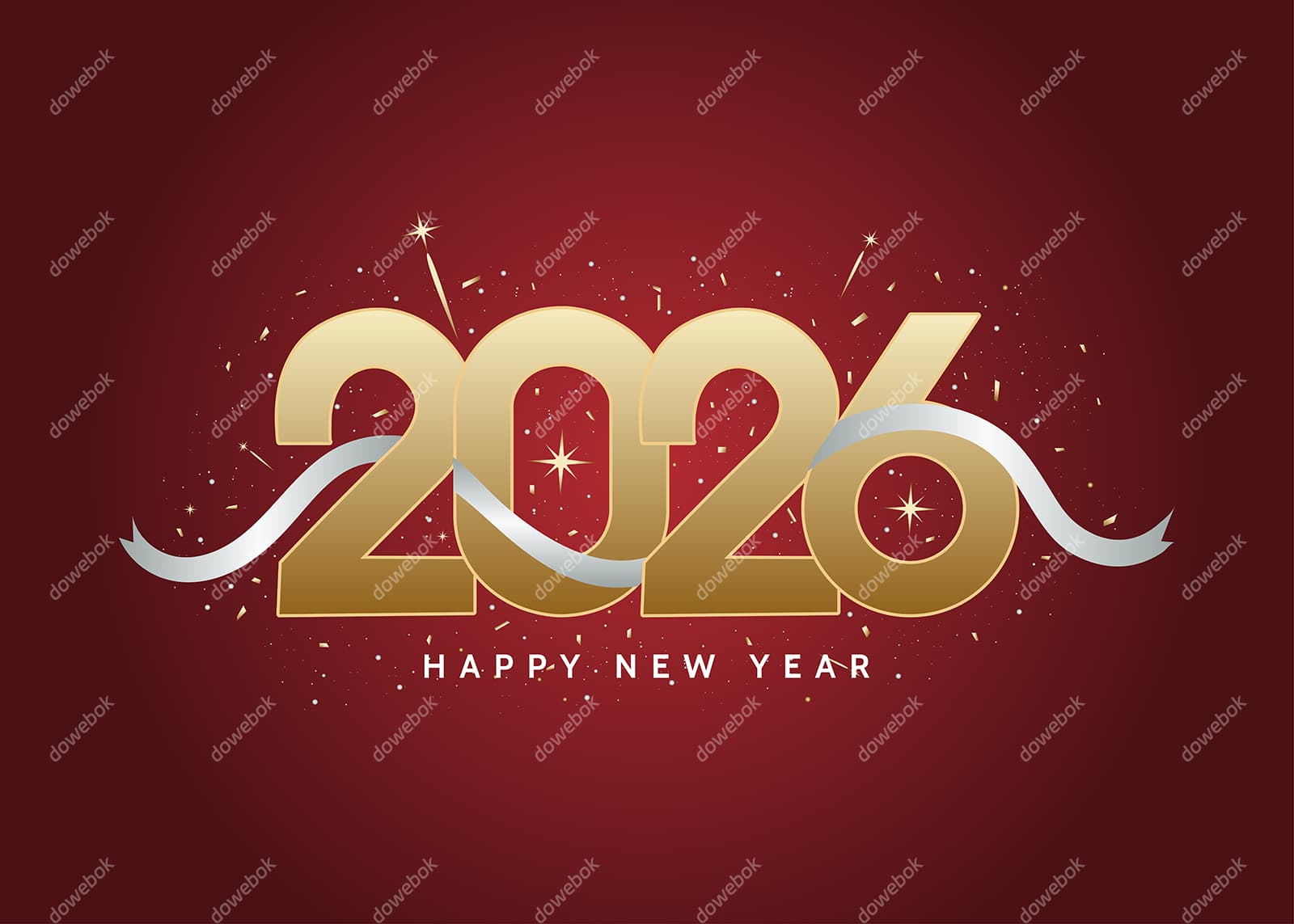
这是一款银白丝带和金色数字设计 2026 新年快乐矢量素材,暗红背景烘托出雅致氛围,鎏金质感的 “2026” 醒目亮眼,银白丝带缠绕其间添了灵动韵律,周围星点光斑似细碎烟火。下方 “Happy New Year” 以简约字体呼应,整体以红金配色 + 柔美元素,既显跨年的精致仪式感,又用闪耀细节透出温馨热烈的节日质感,雅致且鲜活。